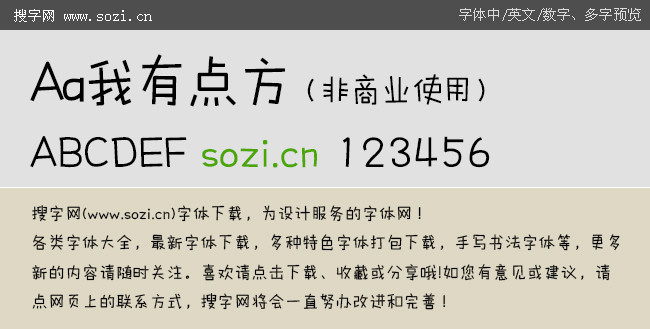
Aa我有點(diǎn)方
搜字網(wǎng)給大家提供一款A(yù)a我有點(diǎn)方(非商業(yè)使用)中文字體下載,該字體是一款個(gè)性的藝術(shù)字體,字體充滿變化,童趣十足,具有很好的視覺(jué)感,適用于平面宣傳設(shè)計(jì)、網(wǎng)頁(yè)設(shè)計(jì)、海報(bào)設(shè)計(jì)等應(yīng)用(此字體為個(gè)人非商用版,商用可以聯(lián)系QQ:1006760504)。